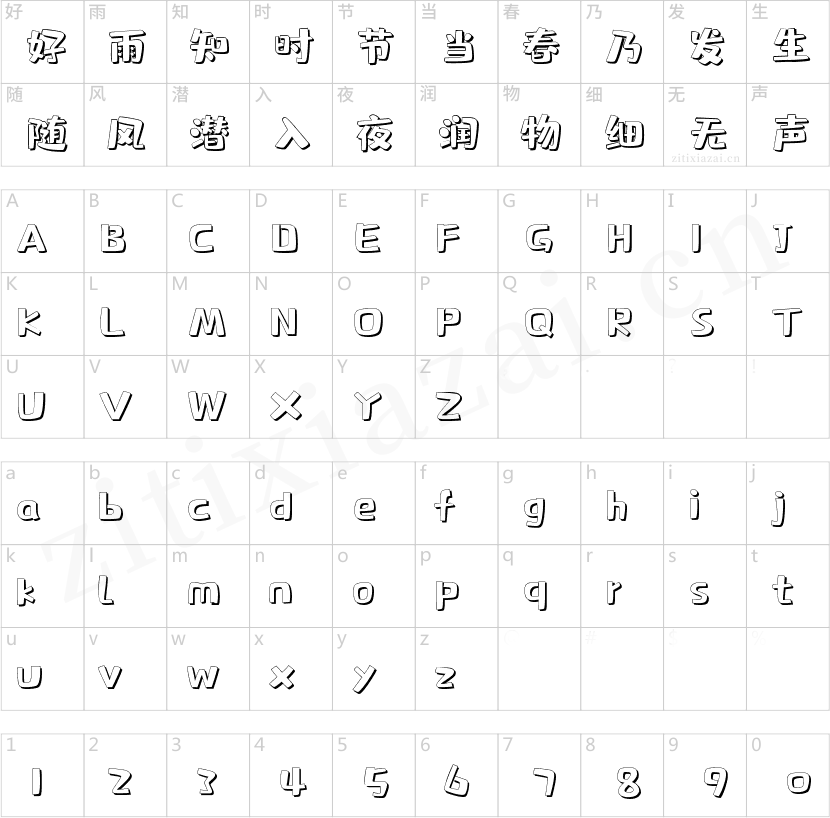
字魂肥宅快乐体
字魂肥宅快乐体,这款字体结构工整、笔画清晰,兼顾美观与易读性,适用于标题、正文、海报、包装、LOGO 等多种场景。字形优雅稳定,风格百搭耐看,适配日常排版与创意设计,让文字呈现更舒适、更具质感。字魂肥宅快乐体一笔一画,皆是细节,以均衡的比例、流畅的线条打造舒适视觉体验,字形端正大气,风格简约现代。无论是商业设计、品牌宣传还是日常排版,都能轻松驾驭,让文字更有格调与力量。字魂肥宅快乐体字体下载。